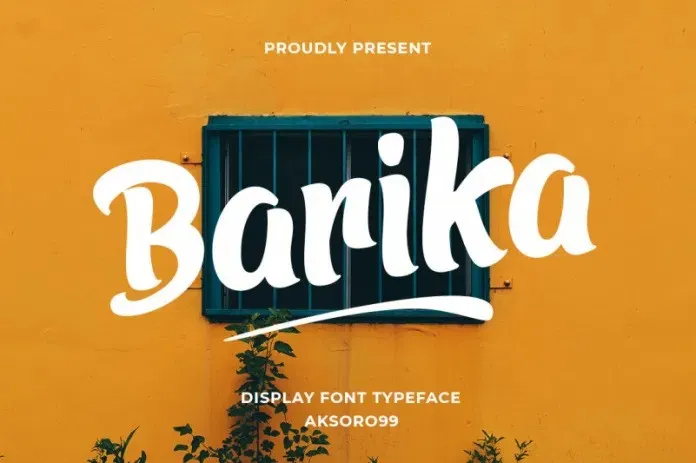
Barika Font – Download Grátis
A fonte ‘Barika Font’ é uma criação simplificada, orgânica e bold para uso em designs visuais modernos. Fabricada pela Aksoro 99 Nugroho através do 99designs, esta fonte de display está equipada para uso em uma variedade de ambientes gráficos, desde identidades corporativas até anúncios publicitários e selos. Ela é ideal para criar slogans impactantes em logotipos ou como o cabeçalho principal no seu site ou revista. A Barika também pode ser usada para criar uma aparência atraente em etiquetas, materiais de embalagem, cartazes e até mesmo estampas em t-shirts. O design da fonte Barika foi projetado para complementar sua marca de forma elegante, permitindo que seja usada em qualquer projeto que exija um ar chamativo.